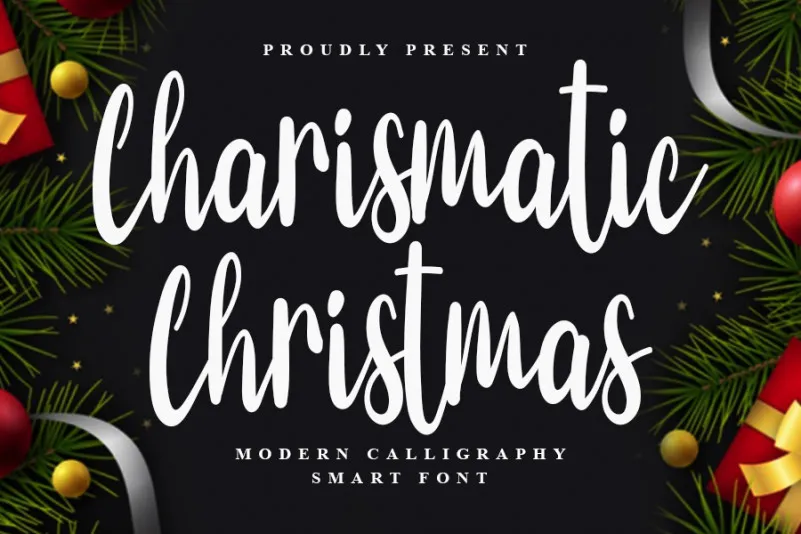
Charismatic Christmas Script Font – Download Grátis
A Charismatic Christmas Script Font é uma tipografia script que traz alegria e entusiasmo para qualquer projeto gráfico. Com sua linha base dançante, ela adiciona um toque pessoal à sua próxima criação de design. É perfeita para aqueles momentos festivos ou natalinos em seu trabalho. Essa fonte é ideal para adicionar uma pitada especial e personalizada ao seu próximo design gráfico, seja para cartões de Natal, letras de música ou qualquer outro elemento decorativo que você possa usar. Seja qual for o projeto, a Charismatic Christmas Script Font certamente dará um toque inconfundível de festividade e entusiasmo.